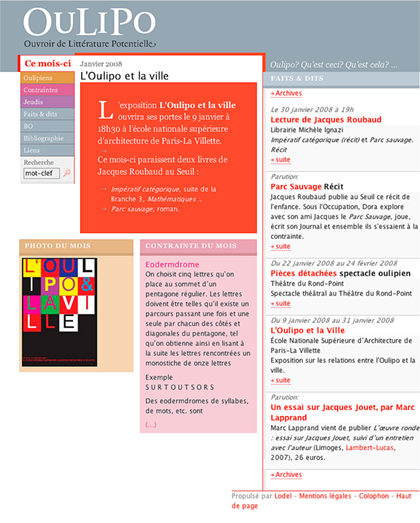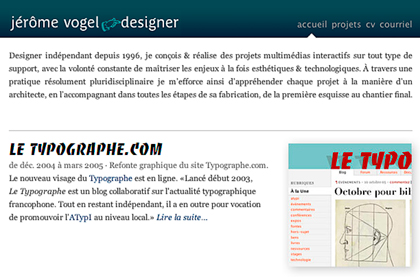
Qu’est-ce que l’Oulipo ?
Marcel Bénabou & Jacques Roubaud OULIPO ? Qu’est ceci ? Qu’est cela ? Qu’est-ce que OU ? Qu’est-ce que LI ? Qu’est-ce que PO ?
OU c’est OUVROIR, un atelier. Pour fabriquer quoi ? De la LI.
LI c’est la littérature, ce qu’on lit et ce qu’on rature. Quelle sorte de LI ? La LIPO.
PO signifie potentiel. De la littérature en quantité illimitée, potentiellement productible jusqu’à la fin des temps, en quantités énormes, infinies pour toutes fins pratiques.
QUI ? Autrement dit qui est responsable de cette entreprise insensée ? Raymond Queneau, dit RQ, un des pères fondateurs, et François Le Lionnais, dit FLL, co-père et compère fondateur, et premier président du groupe, son Fraisident-Pondateur.
Que font les OULIPIENS, les membres de l’OULIPO (Calvino, Perec, Marcel Duchamp, et autres, mathématiciens et littérateurs, littérateurs-mathématiciens, et mathématiciens-littérateurs) ? Ils travaillent. (Lire la suite ici)
Historique de l’oulipo
Histoire :
L’Ouvroir de Littérature Potentielle (OuLiPo) a été fondé, Le 24 novembre 1960, par François Le Lionnais, Raymond Queneau et une dizaine de leurs amis écrivains et/ou mathématiciens et/ou peintres : Albert-Marie Schmidt, Jean Queval, Jean Lescure, Jacques Duchateau, Claude Berge et Jacques Bens selon le tapuscrit de ce dernier, secrétaire définitivement provisoire du début. La réunion fondatrice a eu lieu au restaurant “Le Vrai Gascon”, 82 rue du Bac à Paris.
Le propos était d’inventer de nouvelles formes poétiques ou romanesques, résultant d’une sorte de transfert de technologie entre Mathématiciens et Ecriverons (sic).
Au départ le Séminaire de Littérature Expérimentale devaient s’inclure dans l’Accommission des Compositions du Collège de Pataphysique, chaque séministe ayant le titre de Dataire. (Lire la suite ici)
jérôme vogel | graphiste au service des contraintes
Et c’est en voyageant en pays d’Oulipo et redécouvrant le collège de Pataphysique que je me suis demandé «mais qui a pu réaliser un site aussi élégant, rigoureux et ergonomique (dans la navigation)». Direction le Colophon où je découvre Jérôme Vogel que nous connaissions déjà pour sa réalisation du site de TYPOGRAPHE.COM . J’aime infiniment la délicatesse des détails typographiques, la distribution des blancs, les contrastes superbement maitrisés, et le bon sens logique de ses interfaces de navigation. Tout cela n’est bien sûr possible que par une expertise des plus professionnelle des css, et Jérôme en fait une démonstration magistrale. Où l’on s’aperçoit également qu’un bon site avec du contenu intelligent gagne en visibilité grâce à l’outil typographique.